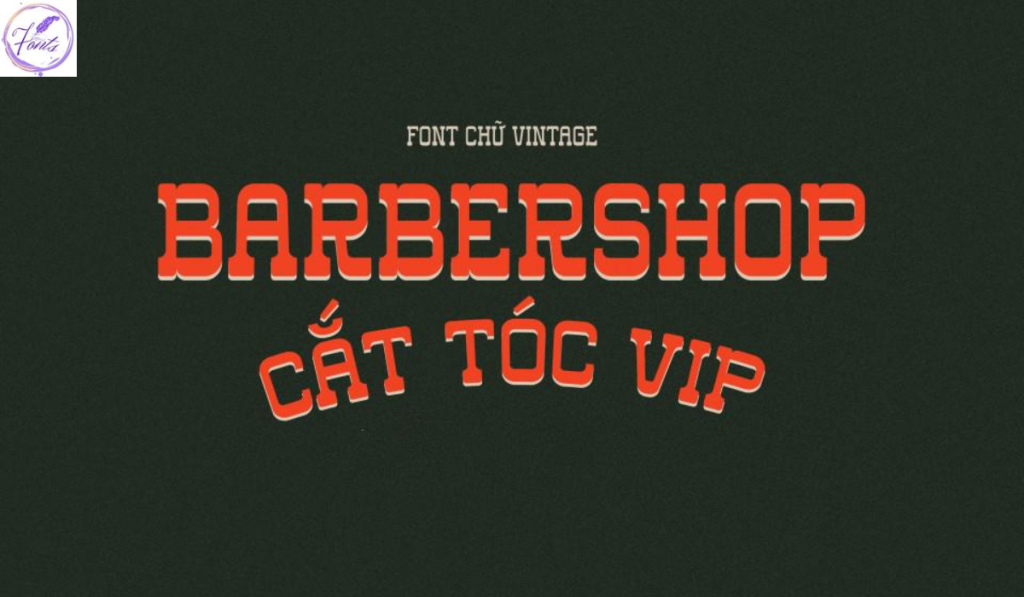
Font Barbershop việt hóa 5 font
Tác giả: Hustle Supply Co.
Ngày phát hành: 2021
Ngôn ngữ: Hỗ trợ nhiều ngôn ngữ, bao gồm Tiếng Việt, Tiếng Anh, và nhiều ngôn ngữ khác
Bộ Font: Barbershop
Phân loại: Cá tính, độc đáo
Kiểu chữ: Có chân, không chân, viết tay
Độ dày: Regular, Bold
Font barbershop là một font chữ độc đáo mang phong cách vintage, được ra mắt vào năm 2021.